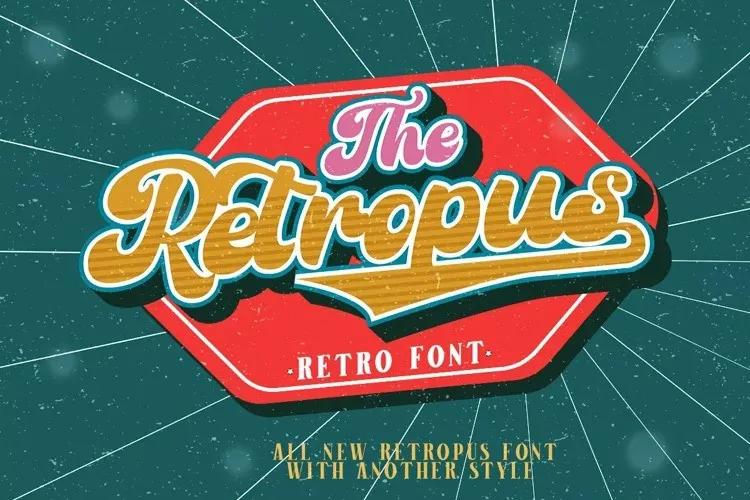
A Retropus Font é uma sugestiva seleção de letras cursivas que captura a essência do estilo retro, misturado com técnicas de escrita à mão. Inspirada na natureza ligeiramente desbotada e encantadora dos anos 80, essa fonte expressa um espírito leve e positivo. Os detalhes sutis, como as swashes ou extremidades estilizadas nas letras finais, conferem ao Retropus Font uma personalidade única, tornando-o perfeito para criar belas mensagens vintage em poucos segundos. Esta fonte é ideal tanto para logotipos quanto para adicionar um toque artesanal aos cartões de social media e cartazes. Ela também se destaca como uma opção atraente para etiquetas de produtos, cabeçalhos de páginas, mensagens personalizadas em cartões de boas-vindas e até mesmo para conteúdo digital de redes sociais. Em suma, o Retropus Font é perfeito tanto para aqueles que buscam um toque nostálgico no design de logotipos quanto para designers que desejam inserir uma nota autêntica em qualquer aplicação visual da sua marca.